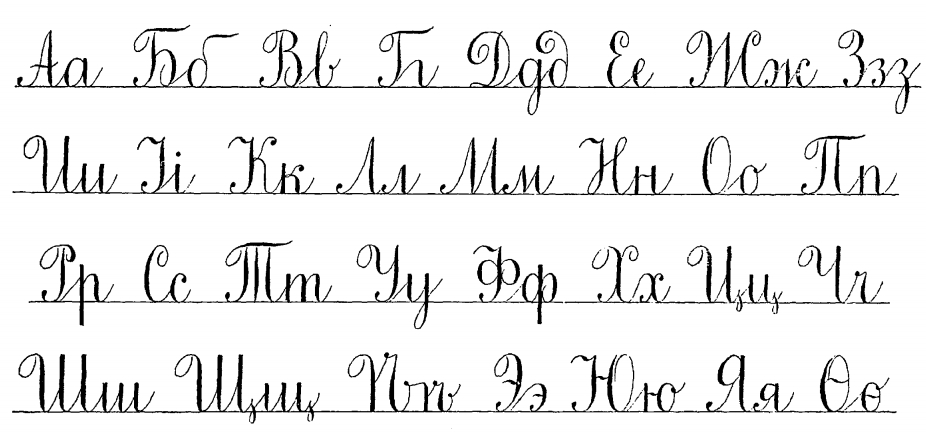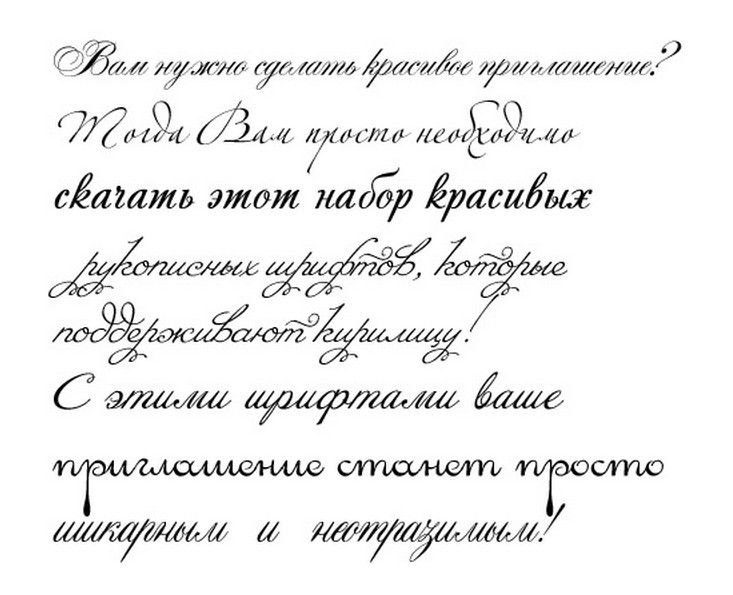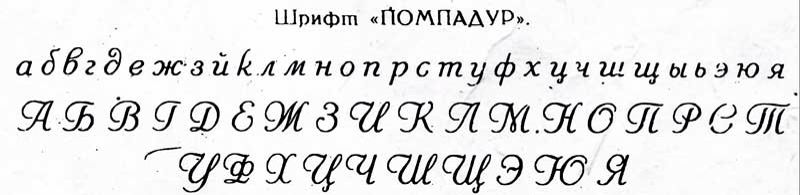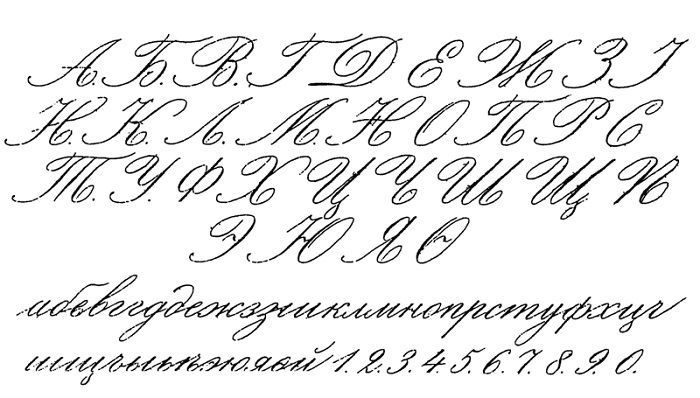
Шрифт красивый курсив русский: Рукописные шрифты — русские скачать бесплатно
Красивые шрифты на русском языке (кириллица)
Нетривиальное оформление ника и текста в аккаунте с помощью красивых, необычных шрифтов в
первую очередь привлекает внимание пользователей «Инстаграма» и других социальных сетей.
Строгие шрифты, уместные для информационных ресурсов и коммерческих сайтов, в соцсетях
- оригинальные шрифты для написания русских текстов – «Кириллический хаос» или «Квадратиш»;
- броские шрифты для выделения слов с использованием латиницы;